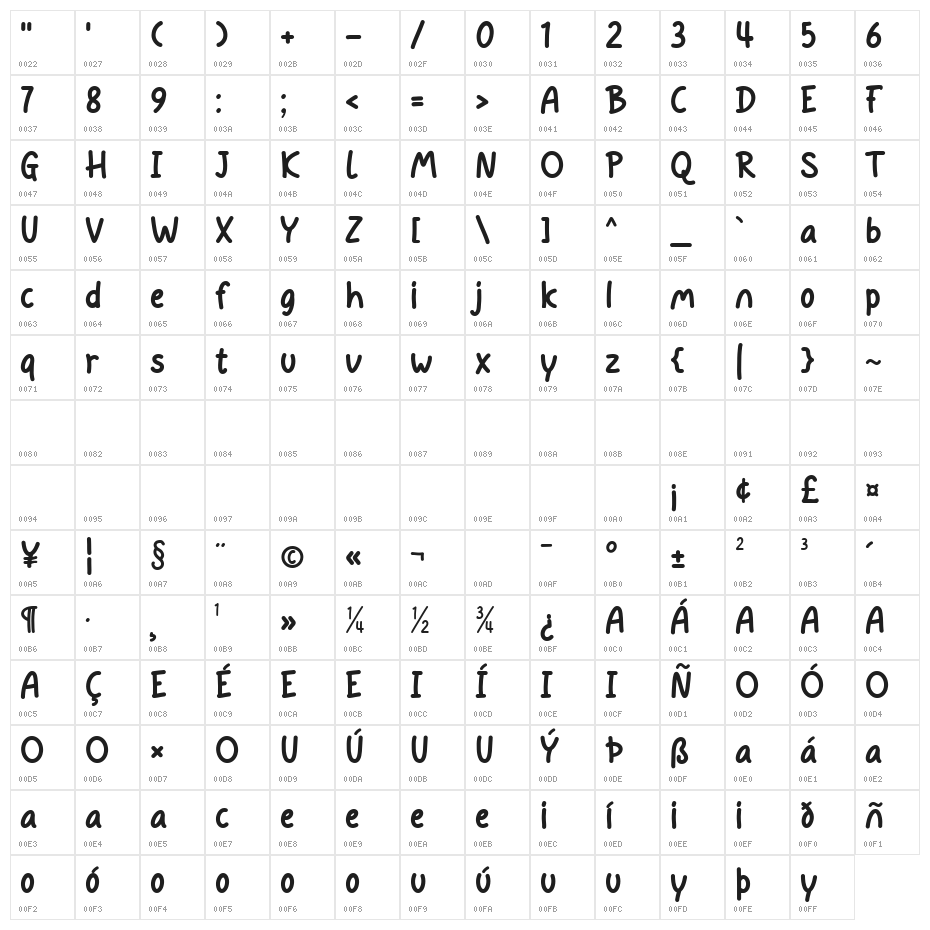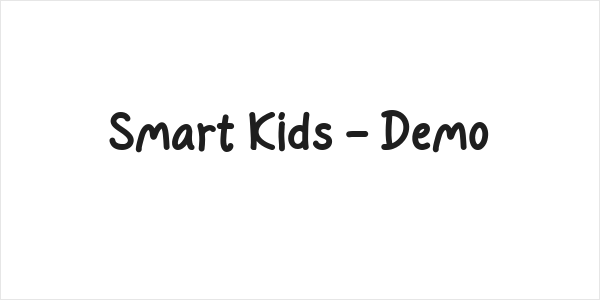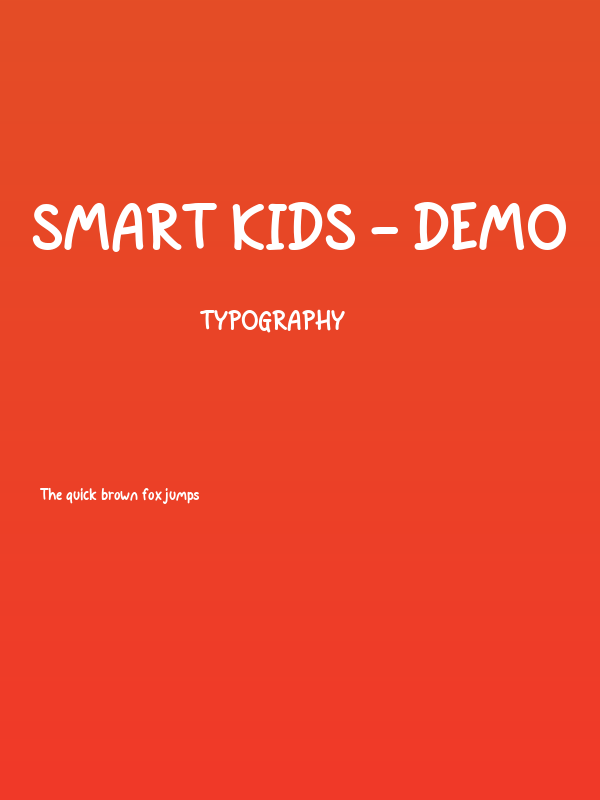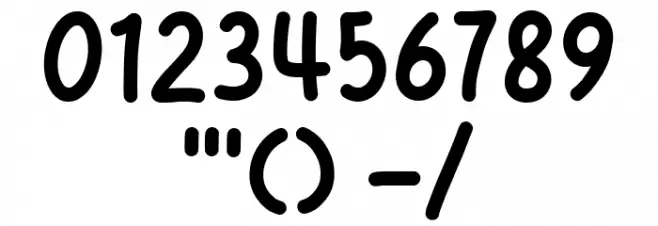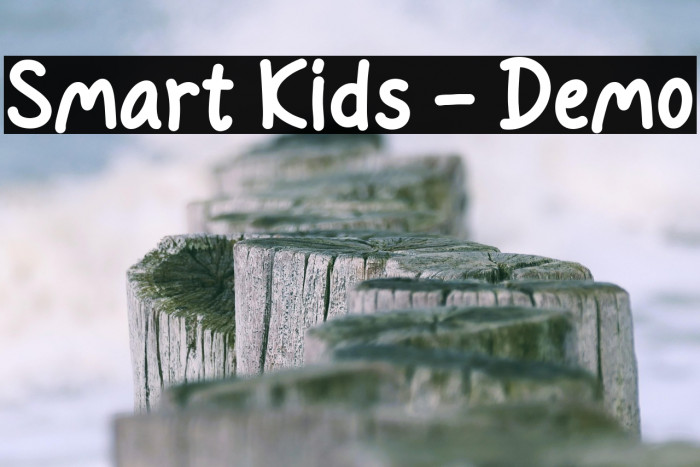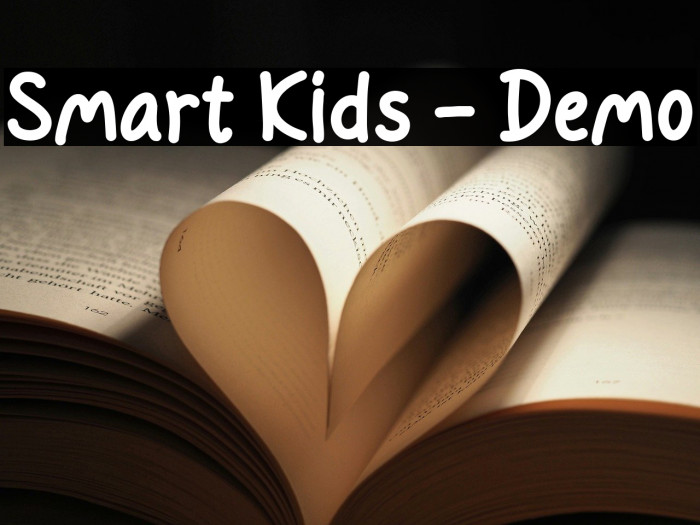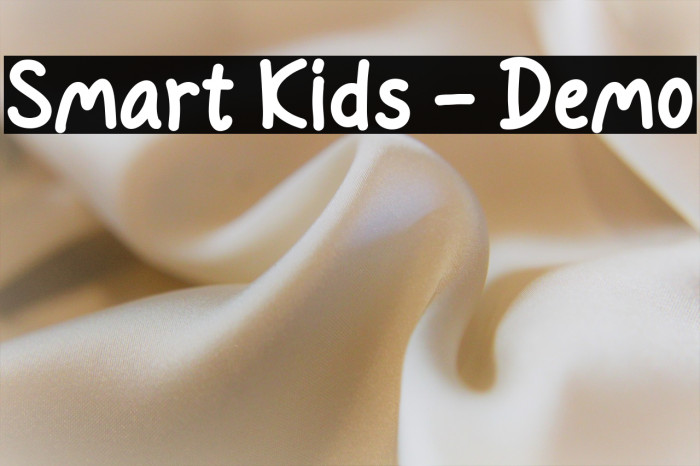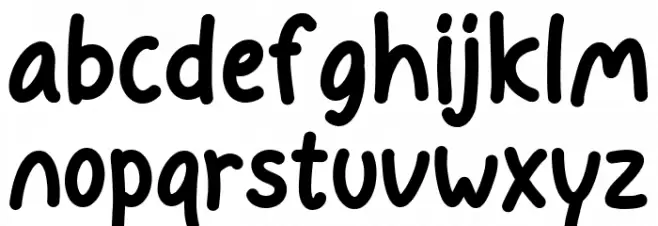
Smart Kids - Demo Font
| Gesamtstil | Playful |
| Anwendungsfall | Headlines, Logos, Children's materials |
| Vorgeschlagene Projekte | Ideal for children's books, educational materials, playful branding, and creative projects. |